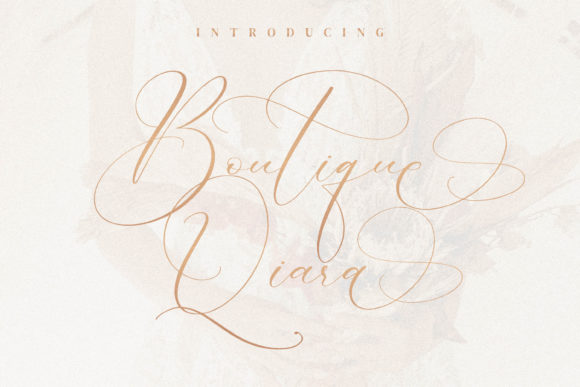
Boutique Qiara
適切なデザイン要素を見つけるのは難しい場合がありますが、Boutique Qiaraは作品を即座に引き立てる優れたコレクションを提供します。
POD(オンデマンド印刷)製品、結婚式の招待状、またはソーシャルメディアのグラフィックを作成している場合でも、Boutique Qiaraは理想的です。